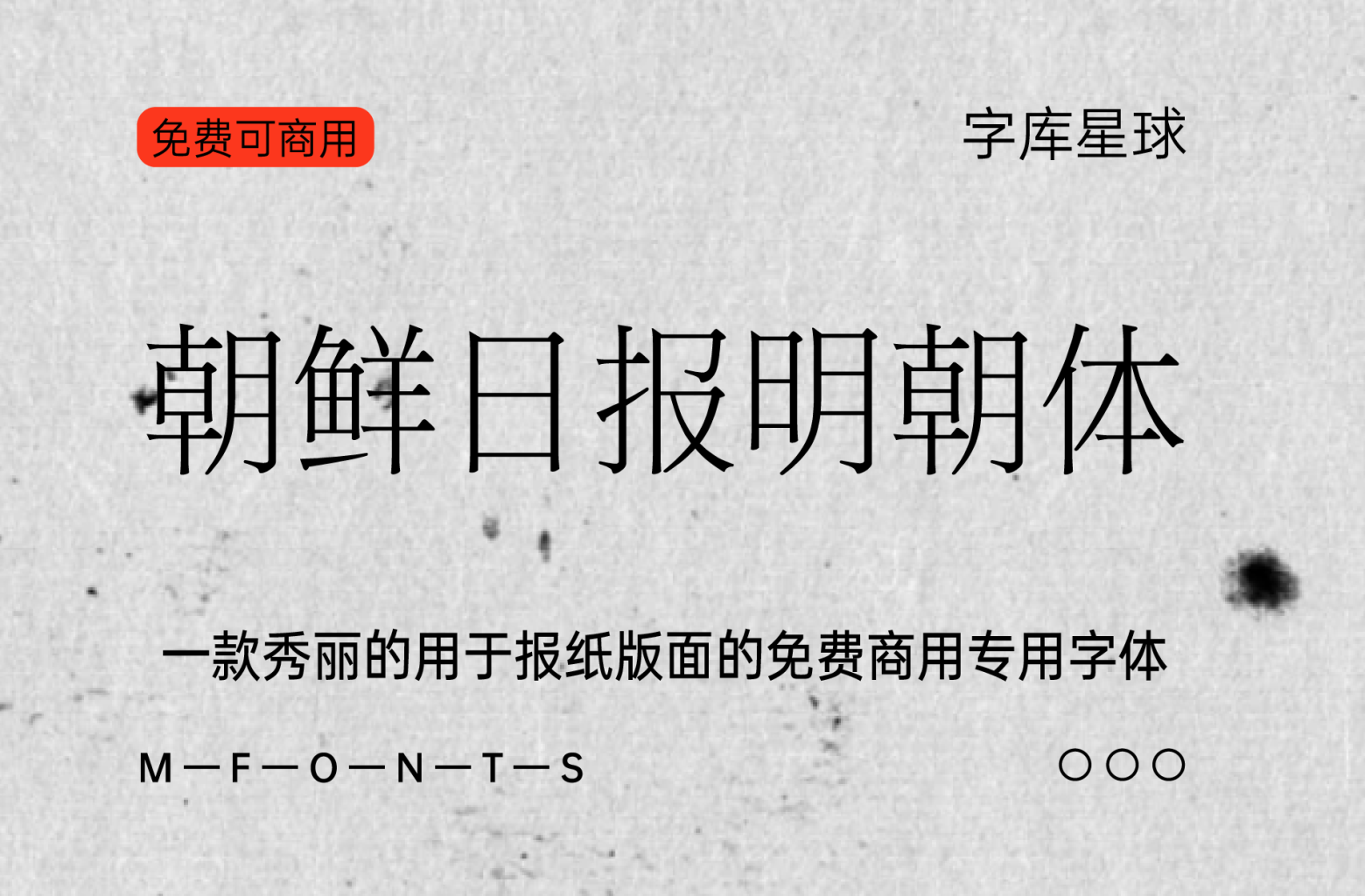
朝鲜日报明朝体
朝鲜日报明朝体是朝鲜媒体集团公开普及了用于报纸版面的专用字体。
《朝鲜日报明朝体》是1999年朝鲜日报书体开发研究所与《桑德尔交流》共同制作的书体,之后在本公司根据匠的精神,对每一个文字进行了补充,提高了完成度。小尺寸使用也容易读造型美出色,除了受到读者的喜爱以外,也得到了专家的好评。Windows和Mac都可以使用。